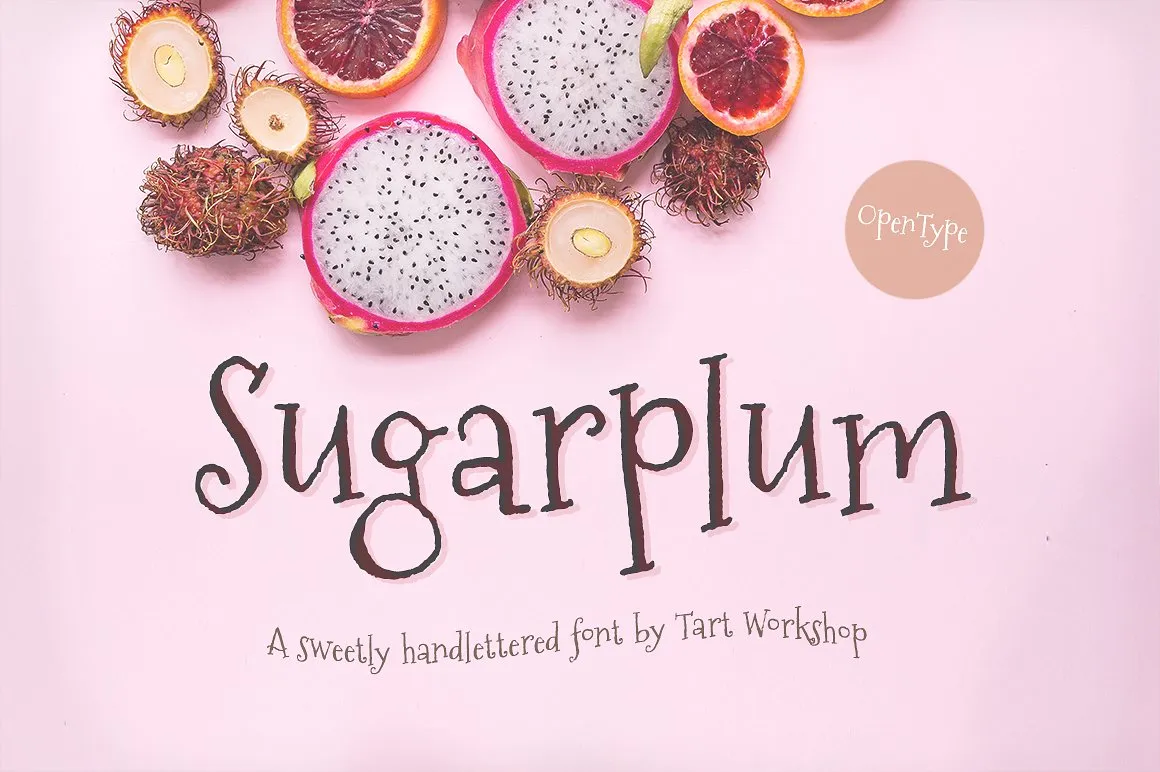
Sugarplum Font
Descubra uma nova adição para seu arsenal de fontes com Sugarplum Font! Desenvolvida pelo Tart Workshop, esta fonte premium está disponível gratuitamente hoje na Creativemarket. Com suas formas alternativas completas e ligaturas automaticas, a Sugarplum é perfeita para transpor sua letra através do abraço suave de um novo conceito visual. Para tornar seu design ainda mais especial, ela traz uma sensação leve e divertida que promove a ideia de ser gentil e positiva. Esta fonte é ideal para criar mensagens amigáveis ou quando você deseja dar um toque delicado e criativo em qualquer projeto que esteja trabalhando. Aproveite esta oferta limitada e descubra por si mesmo como Sugarplum pode transformar suas criações!